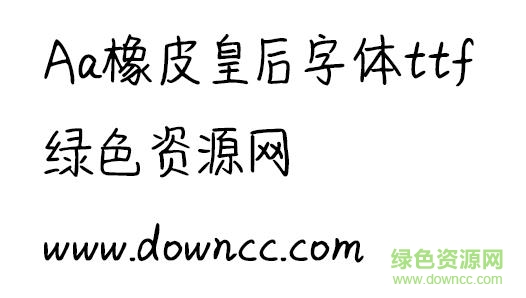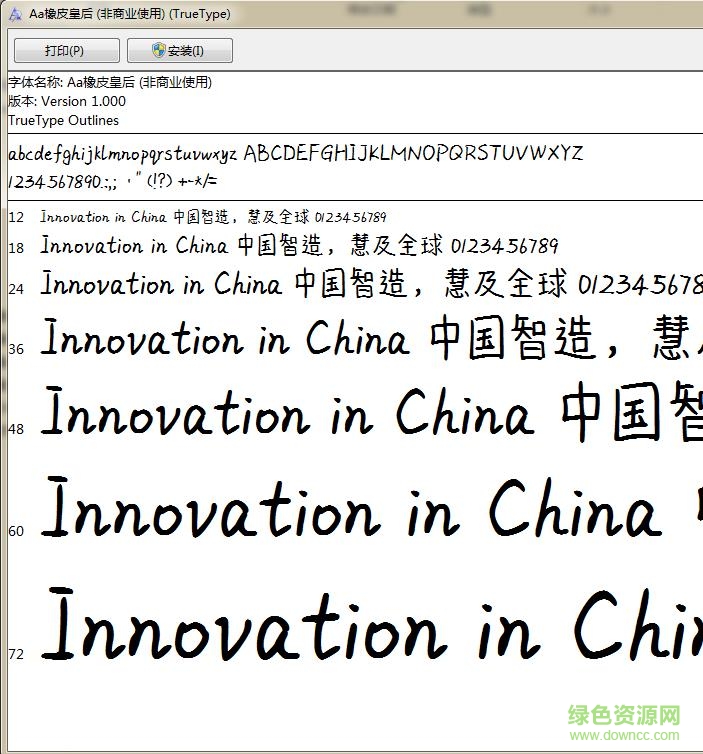
Aa橡皮皇后字體
Aa橡皮皇后字體下載這款字體的效果真的非常不錯(cuò),我們小時(shí)候常常用的橡皮被制作到了字體內(nèi)部,讓你感受到一股歪歪扭扭的有趣視覺效果,挺不錯(cuò)的!快來綠色資源網(wǎng)下載吧!
aa橡皮皇后字體小編點(diǎn)評(píng)
這款字體的樣式將讓你感受到全新的體驗(yàn),字體風(fēng)格十分有趣,在使用的時(shí)候,能夠完成眾多的變換都能夠獲得獨(dú)特的效果哦!
aa橡皮皇后字體ttf特色介紹